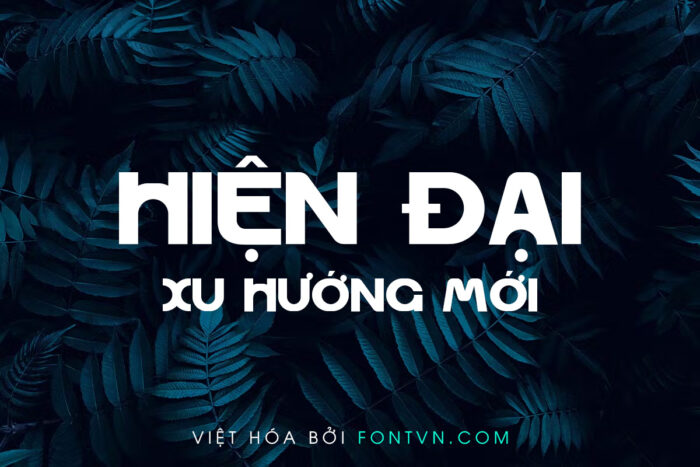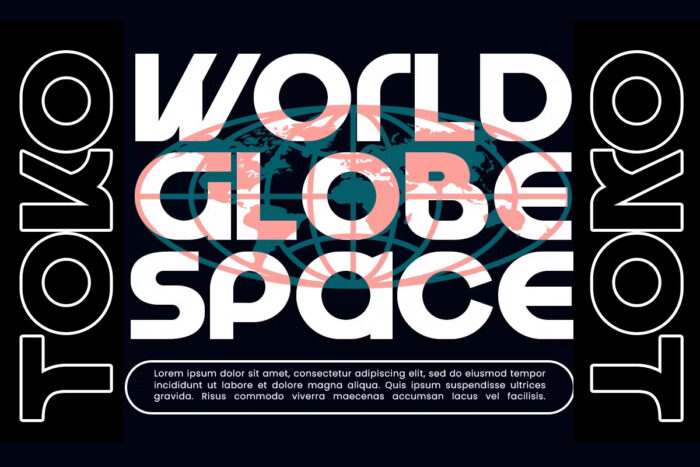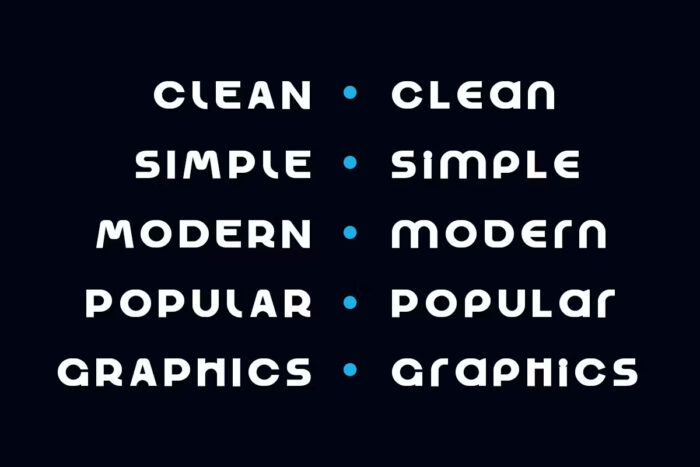
DVN Toko Việt hóa – Font chữ hiện đại phong cách mới lạ
Font chữ Toko là một kiểu chữ sans-serif tối giản và hiện đại. Với các đường nét dày, đều đặn và hình dạng tròn đầy, Toko mang lại cảm giác mạnh mẽ và dễ nhìn. Các ký tự có thiết kế rộng rãi, giúp tăng tính dễ đọc và phù hợp với nhiều mục đích sử dụng khác nhau.
Hình dạng của font chữ Toko thể hiện sự cứng cáp và rõ ràng, với các góc bo tròn mượt mà tạo cảm giác thân thiện và dễ tiếp cận. Đặc điểm này khiến Toko trở thành lựa chọn lý tưởng cho các thiết kế logo, tiêu đề và các tài liệu quảng cáo đòi hỏi sự nổi bật và thu hút sự chú ý.
Ứng dụng của font chữ Toko rất đa dạng. Với phong cách hiện đại và thanh thoát, nó có thể được sử dụng trong thiết kế website, các sản phẩm in ấn như tờ rơi, poster, và các ấn phẩm thương mại. Ngoài ra, Toko cũng phù hợp cho các thiết kế mang tính sáng tạo như bao bì sản phẩm, các dự án thiết kế đồ họa đương đại và truyền thông kỹ thuật số.
Với sự kết hợp giữa tính tối giản và hiện đại, font chữ Toko không chỉ mang lại vẻ đẹp thị giác mà còn đảm bảo tính ứng dụng cao trong nhiều lĩnh vực thiết kế.